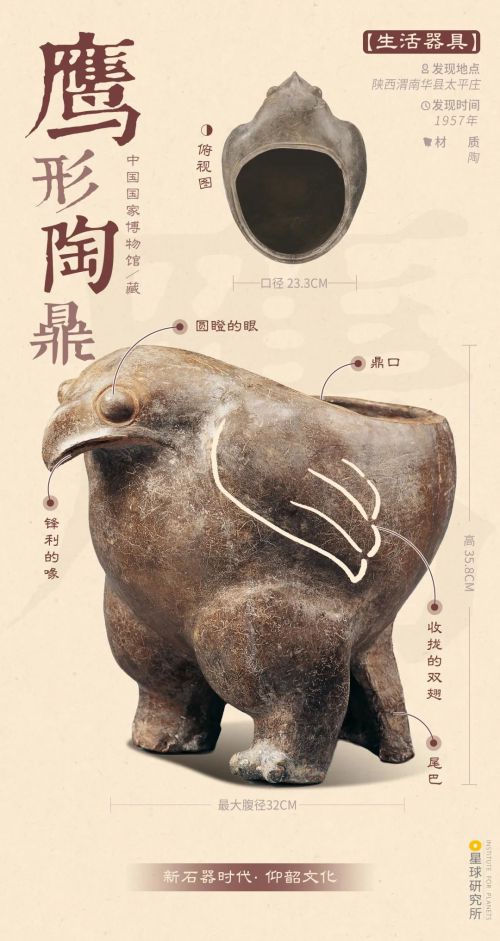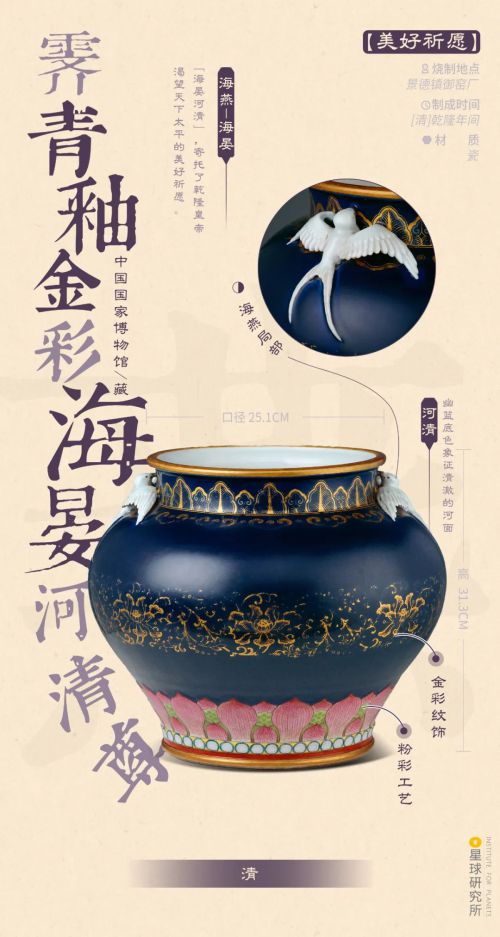
叶根友古刻体是叶根友品牌旗下一款极具中国风的古典书法字体,融合手写风灵动与古刻厚重质感,气质独特。该字体字形方正稳健,重心居中稳重,中宫宽博舒展,尽显端庄大气之态;笔画设计巧具匠心,方头笔画粗细均匀,搭配斜切装饰元素,笔画间断开处理更添古典刻字韵味,细节处彰显个性张力。 叶根友古刻体风格优雅古典,会员商用授权覆盖常规字符集,适用场景广泛。无论是各类标题用字、追求个性的海报设计,还是古籍装帧、传统文创产品等,都能凭借其浓郁的中国风与古刻气质,瞬间提升作品的文化底蕴与视觉吸引力,成为设计中画龙点睛的优质选择。